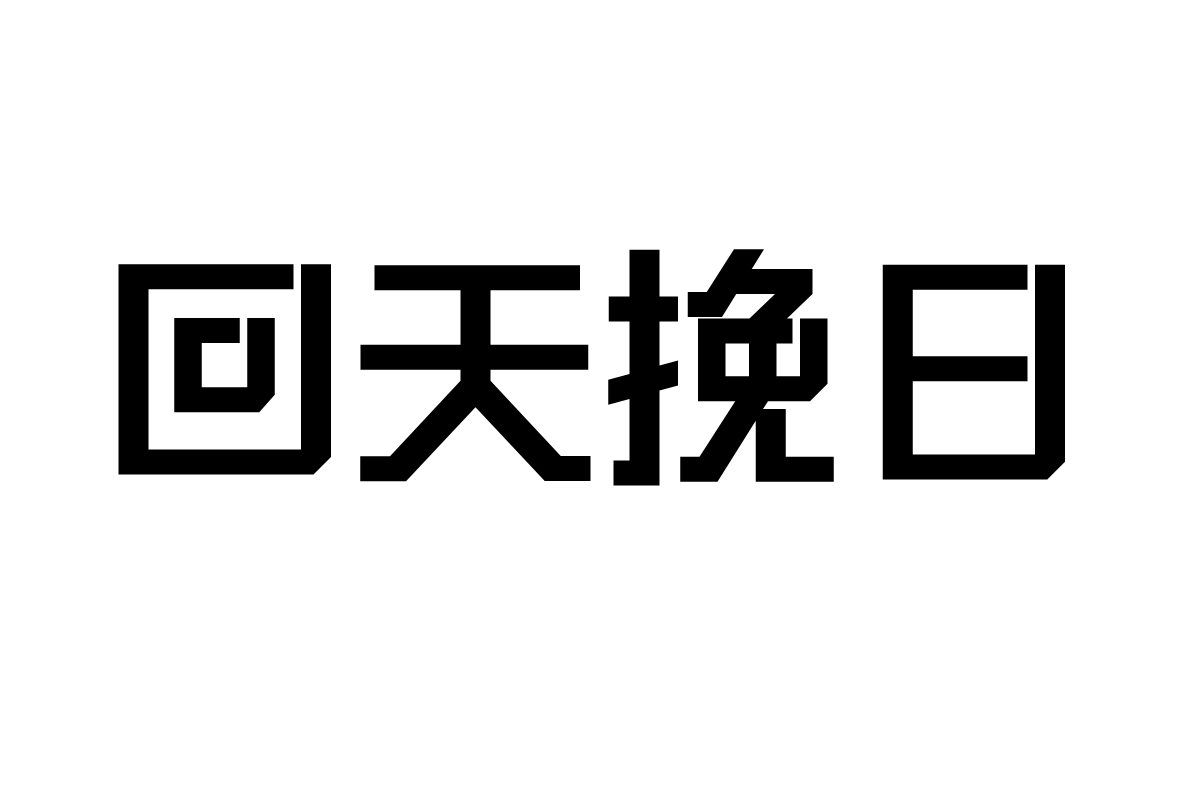
超粗字体是一种非常粗的字体,通常用于标题、广告和标识等。它的设计目的是为了吸引观众的注意力,使信息更加突出。这种字体的特点是线条粗大,形状简单,易于识别。
三极硬朗黑简体是一种特殊的超粗字体,它结合了现代感和传统元素,线条流畅而有力,给人一种坚韧不拔的感觉。这种字体适用于需要传达力量、勇气和决心的场景,如企业标志、品牌宣传等。
超粗字体的优点在于其强烈的视觉冲击力,能够迅速吸引观众的注意力。同时,由于线条粗大,阅读起来也相对容易。然而,过于夸张的字体可能会让人感到不舒服或难以理解,因此使用时需要谨慎。